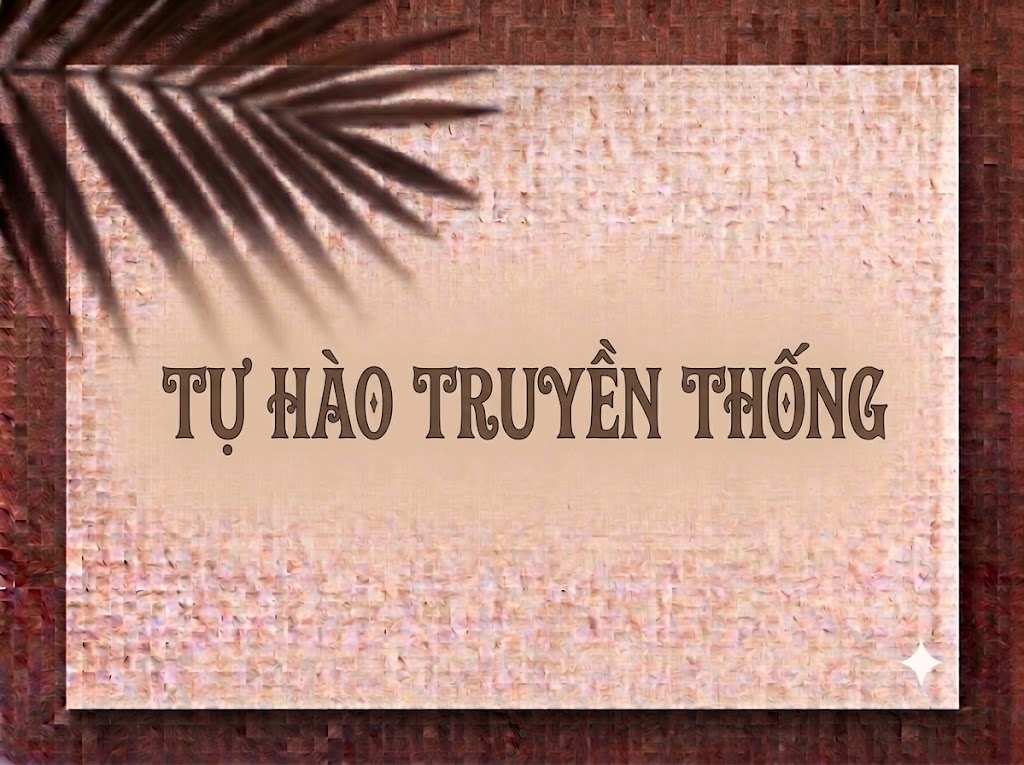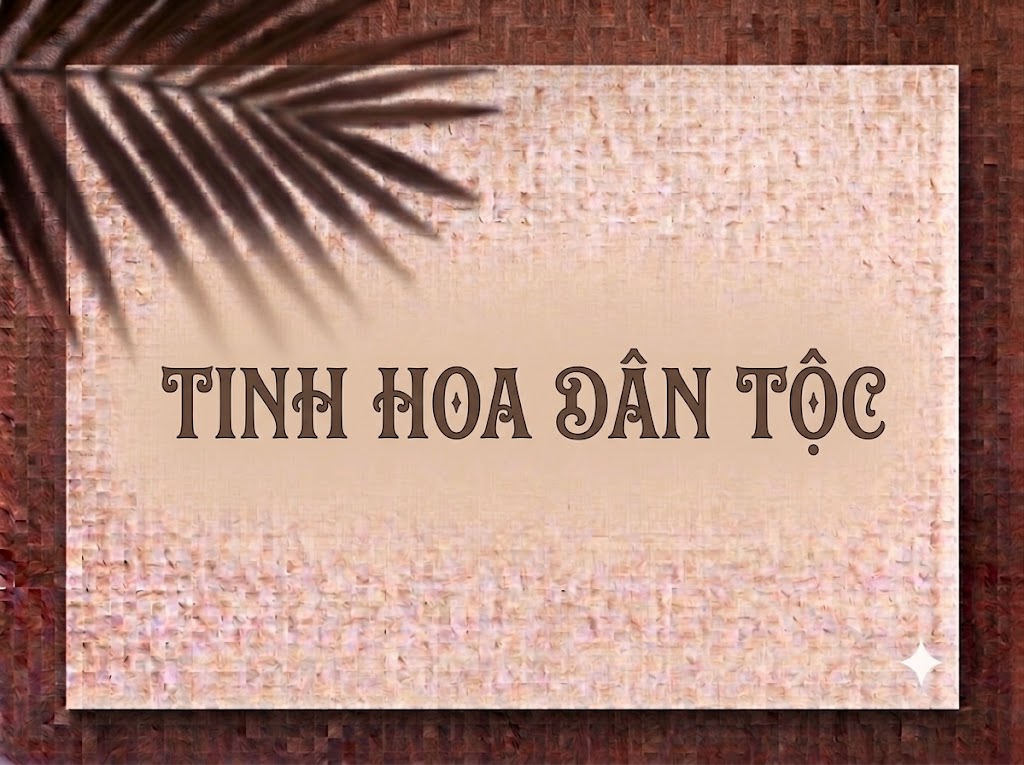
1FTV VIP Christmas Beach
Mỗi mùa lễ hội hay các chiến dịch truyền thông nghỉ dưỡng, việc sở hữu một phông chữ trang trí mang tinh thần vui tươi, phóng khoáng luôn là yếu tố quan trọng để thu hút ánh nhìn của khách hàng. Một dòng tiêu đề độc đáo không chỉ truyền tải thông điệp ngắn gọn mà còn mang đến cảm giác hứng khởi, ấm áp và tràn đầy năng lượng tích cực.
Nếu bạn đang tìm kiếm một phông chữ hiển thị kết hợp giữa không khí Giáng sinh diệu kỳ và tinh thần mùa hè phóng khoáng cho banner khuyến mãi, thiệp chúc mừng, menu quán hay tiêu đề video ngắn, font 1FTV VIP Christmas Beach chính là sự lựa chọn vô cùng thú vị.
Giới thiệu về font 1FTV VIP Christmas Beach
Font 1FTV VIP Christmas Beach là bộ chữ hiển thị trang trí (decorative display) sở hữu phom dáng nhí nhảnh, kết hợp giữa sự ấm áp của không khí Noel và nét rực rỡ, tự do của những kỳ nghỉ biển:
Tên phông chữ: 1FTV VIP Christmas Beach
Được hoàn thiện chỉn chu về mặt kỹ thuật, phông chữ mang lại khả năng hiển thị vô cùng sắc nét. Bạn có thể tự tin phóng lớn chữ trên các ứng dụng đồ họa chuyên nghiệp hay phần mềm dựng video mà không lo gặp tình trạng vỡ nét hay răng cưa.
Đặc điểm nổi bật của phong cách thiết kế VIP Christmas Beach
Sức hút thị giác của font 1FTV VIP Christmas Beach đến từ sự phá cách vui nhộn và các chi tiết uốn xoắn trang trí giàu cảm xúc:
Chi tiết xoắn curlicue độc đáo: Điểm nhấn đắt giá nhất của phông chữ nằm ở phần vòng xoắn ngộ nghĩnh ở các ký tự như
Q,B,R,O,F,J,P,S,D,G. Nét uốn mềm mại này gợi nhớ đến những chiếc kẹo que Giáng sinh hay từng con sóng biển cuộn tròn tươi mát. -
Tinh thần “Christmas Beach” phóng khoáng: Sự pha trộn độc đáo giữa phom dáng lễ hội truyền thống và phong cách du lịch nhiệt đới đem lại làn gió mới mẻ cho các thiết kế truyền thông mùa lễ hội.
Định dạng All-Caps đồng bộ: Hệ thống chữ cái in hoa cùng dãy số từ 0-9 được tạo hình đồng nhất, giúp câu tiêu đề giữ được sự kiên cố, thu hút ánh nhìn ngay từ giây đầu tiên.
Để phông chữ vận hành mượt mà trên cả hệ điều hành Windows lẫn macOS, phiên bản này đã được xử lý kỹ lưỡng về thông số nội tại:
Khoảng cách giữa các chữ (kerning) và độ giãn dòng được tính toán chuẩn xác, giúp các chi tiết nét xoắn khi đứng cạnh nhau không bị dính hay rối mắt.
Tích hợp trọn vẹn bộ chữ cái, dãy chữ số 0-9 phom dáng sinh động cùng hệ thống ký tự đặc biệt, dấu câu thông dụng.
Bản Việt hóa chuẩn chỉnh giúp bạn hoàn toàn yên tâm thiết kế các văn bản tiếng Việt có dấu mà không gặp lỗi nhảy font hay mất ký tự.
Hình ảnh demo thực tế của font 1FTV VIP Christmas Beach
Khả năng hiển thị của phông chữ này được tối ưu rất tốt trên nhiều tỷ lệ kích thước khác nhau:
Kích thước nhỏ (12pt – 24pt): Cấu trúc nét chữ rành mạch giúp bộ chữ và dãy số vẫn hiển thị rõ ràng trên các giao diện màn hình di động.
Kích thước lớn (36pt – 72pt): Đây là đất diễn lý tưởng nhất để 1FTV VIP Christmas Beach phô diễn toàn bộ sự vui nhộn, ngọt ngào của các nét xoắn trang trí, tạo tác động thị giác mạnh mẽ cho các dòng headline chính.
Ứng dụng trong thiết kế đồ họa và làm video
Sở hữu nét cá tính tươi vui và độc đáo, font 1FTV VIP Christmas Beach mở ra không gian ứng dụng phong phú:
Video ngắn (TikTok, Reels, Shorts): Dáng chữ trang trí bắt mắt này hiển thị rất đẹp trên khung hình đứng tỷ lệ 9:16. Cực kỳ ăn nhập với các video vlog du lịch, tiệc tùng lễ hội, review ẩm thực hay hướng dẫn làm đồ handmade.
Banner Flash Sale & E-commerce: Lựa chọn hàng đầu để giật tít các chiến dịch khuyến mãi mùa lễ, chương trình “Tropical Christmas”, “Year-End Sale” trên Shopee, Lazada, TikTok Shop hay Facebook Banner.
Thiết kế Thiệp mừng & Bao bì sản phẩm: Hoàn hảo cho các mẫu thiệp chúc mừng, nhãn mác quà tặng, bao bì đồ uống, menu café/beach bar hay poster sự kiện âm nhạc ngoài trời.
Ảnh thu nhỏ YouTube (Thumbnail): Vũ khí tuyệt vời cho các kênh làm nội dung về du lịch, âm nhạc tươi vui, vlog đời sống nhờ giao diện thu hút và dễ gây ấn tượng.